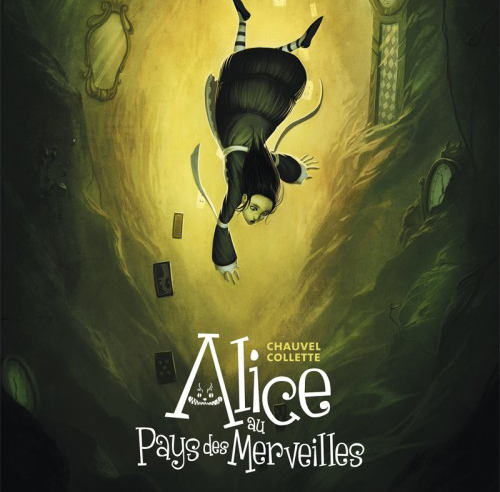
Font name: | Grenouille |
Author: | Louis Rigaud |
Note by Louis Rigaud | |
Typographie réalisée pour un livre de cuisine, à voir sur mon site : http://ludocube.fr Pour tout usage commercial, merci de me contacter; louisrigaud@gmail.com L'illustration est tiré de la couverture d'Alice au pays des merveilles (Xavier Collette) paru chez Drugstore. Font created for a cooking book, see more on my website : http://ludocube.fr for commercial use, please contact me : louisrigaud@gmail.com The illustration is from Alice au pays des merveilles (Xavier Collette) publish by Drugstore. |